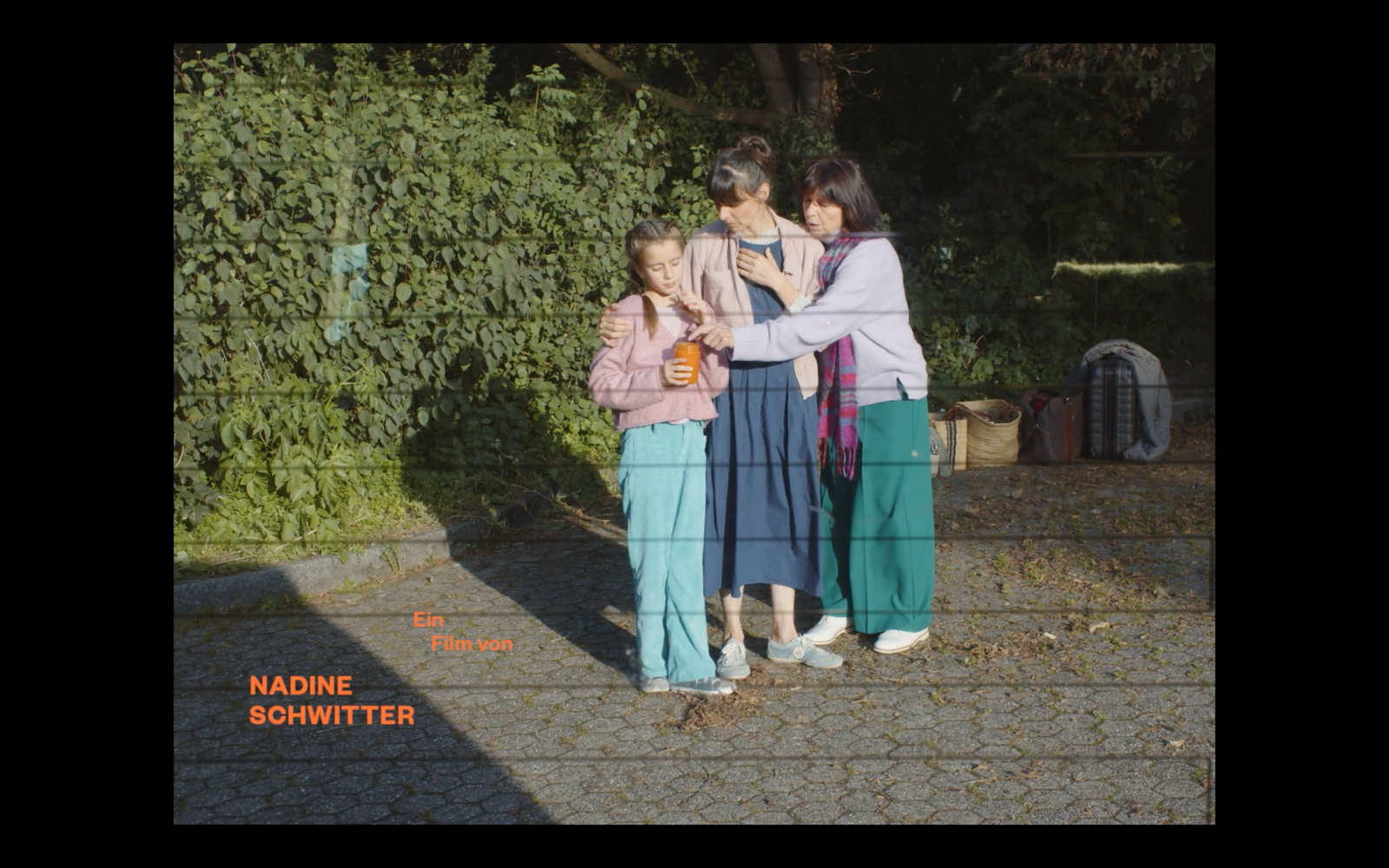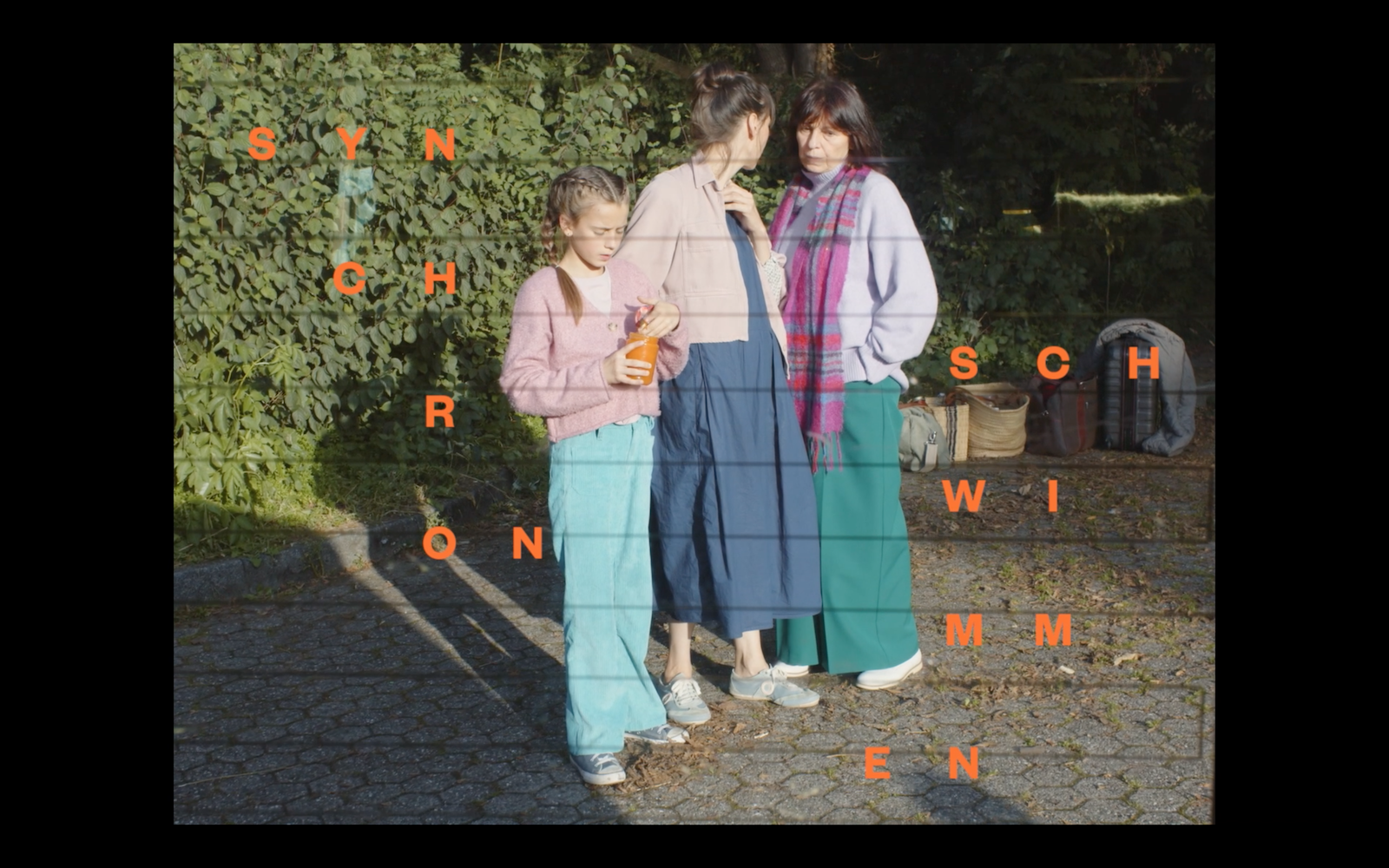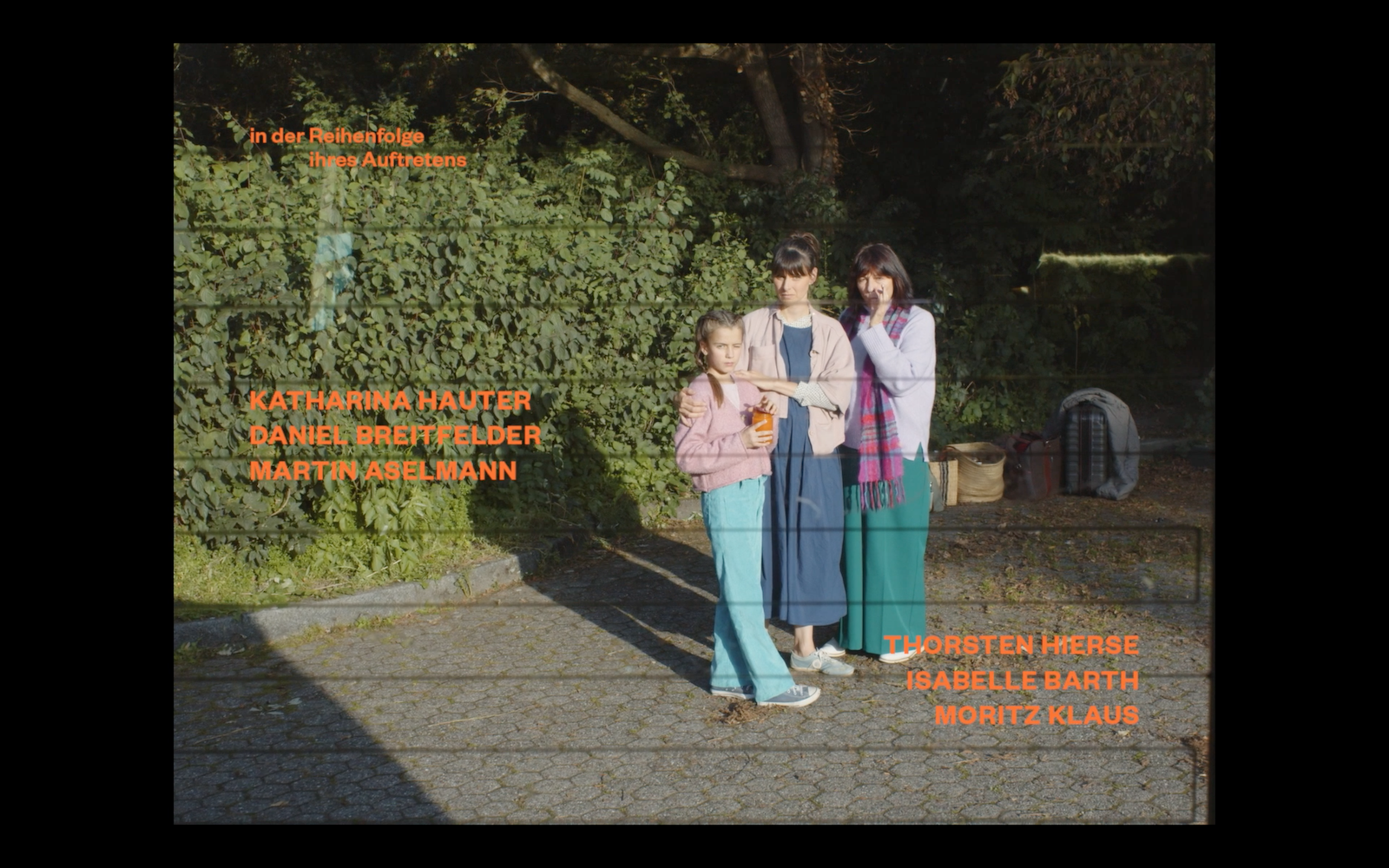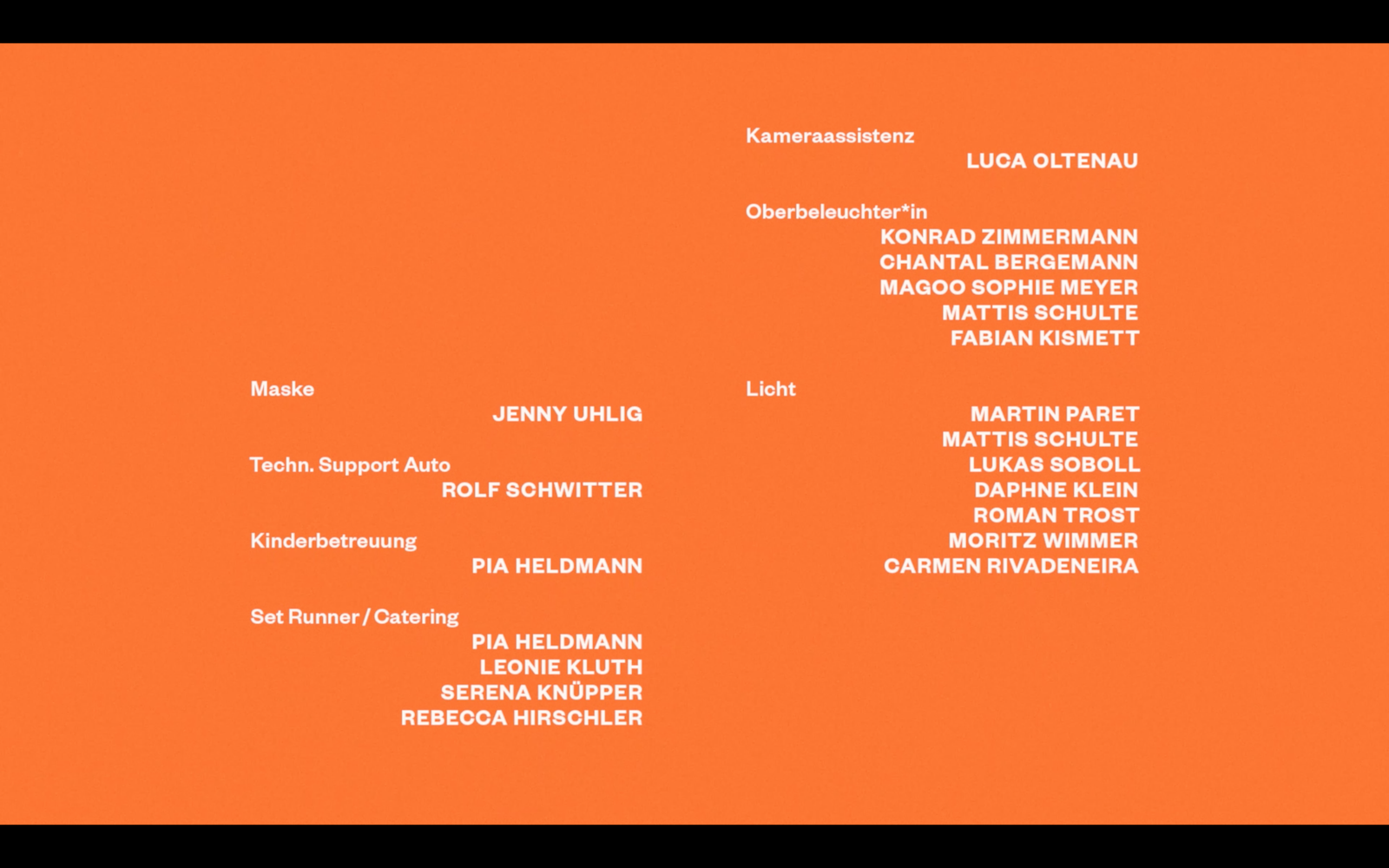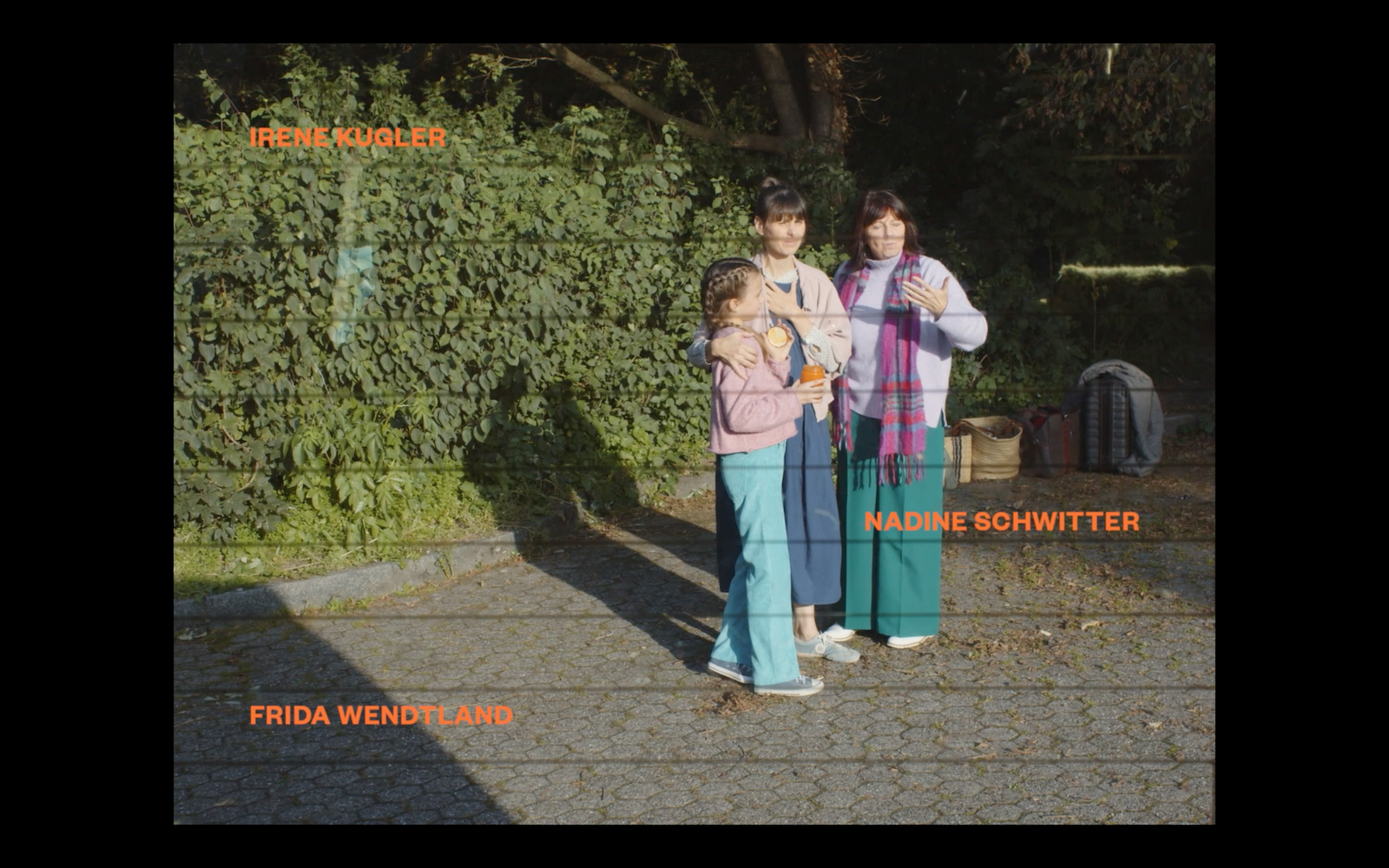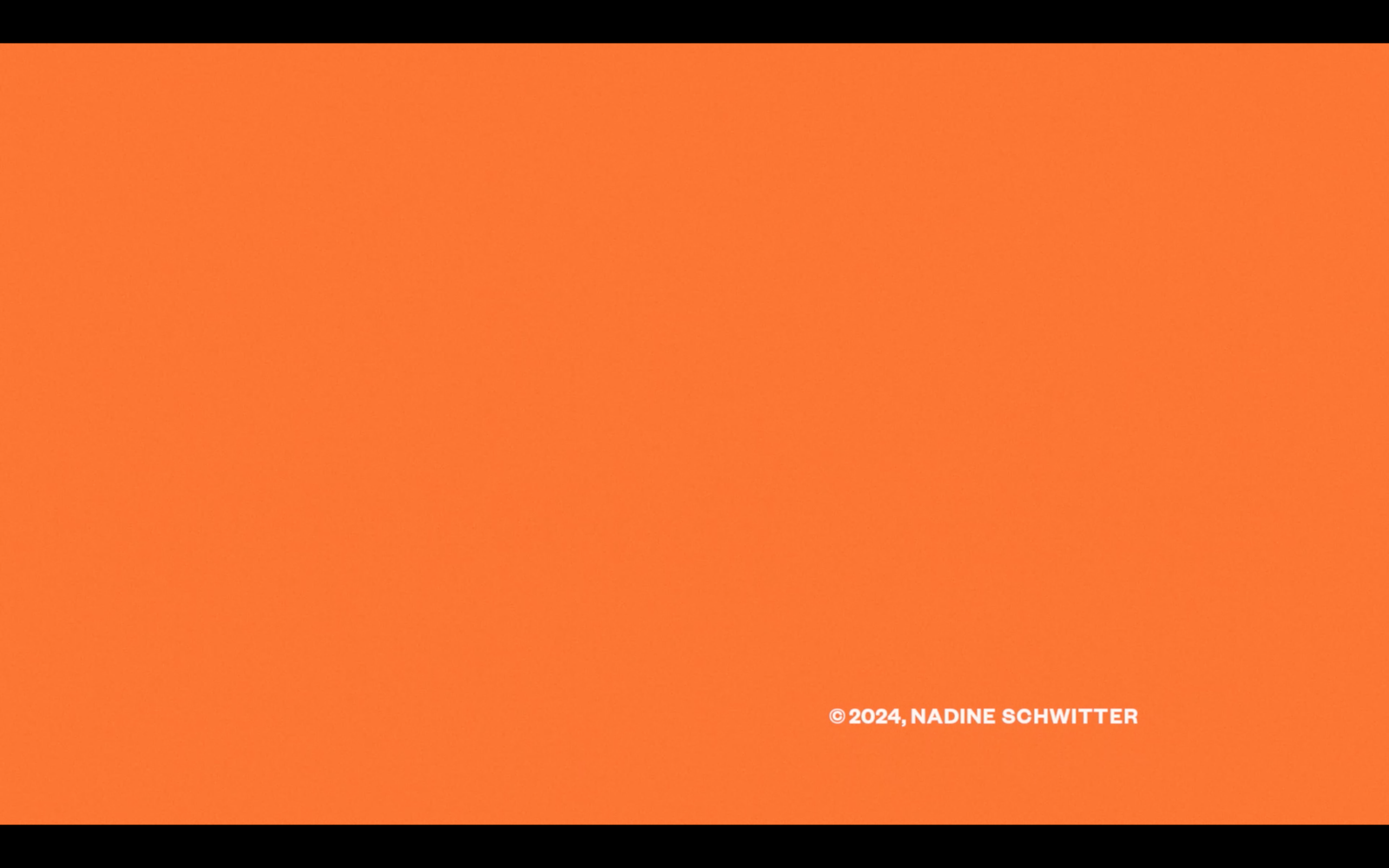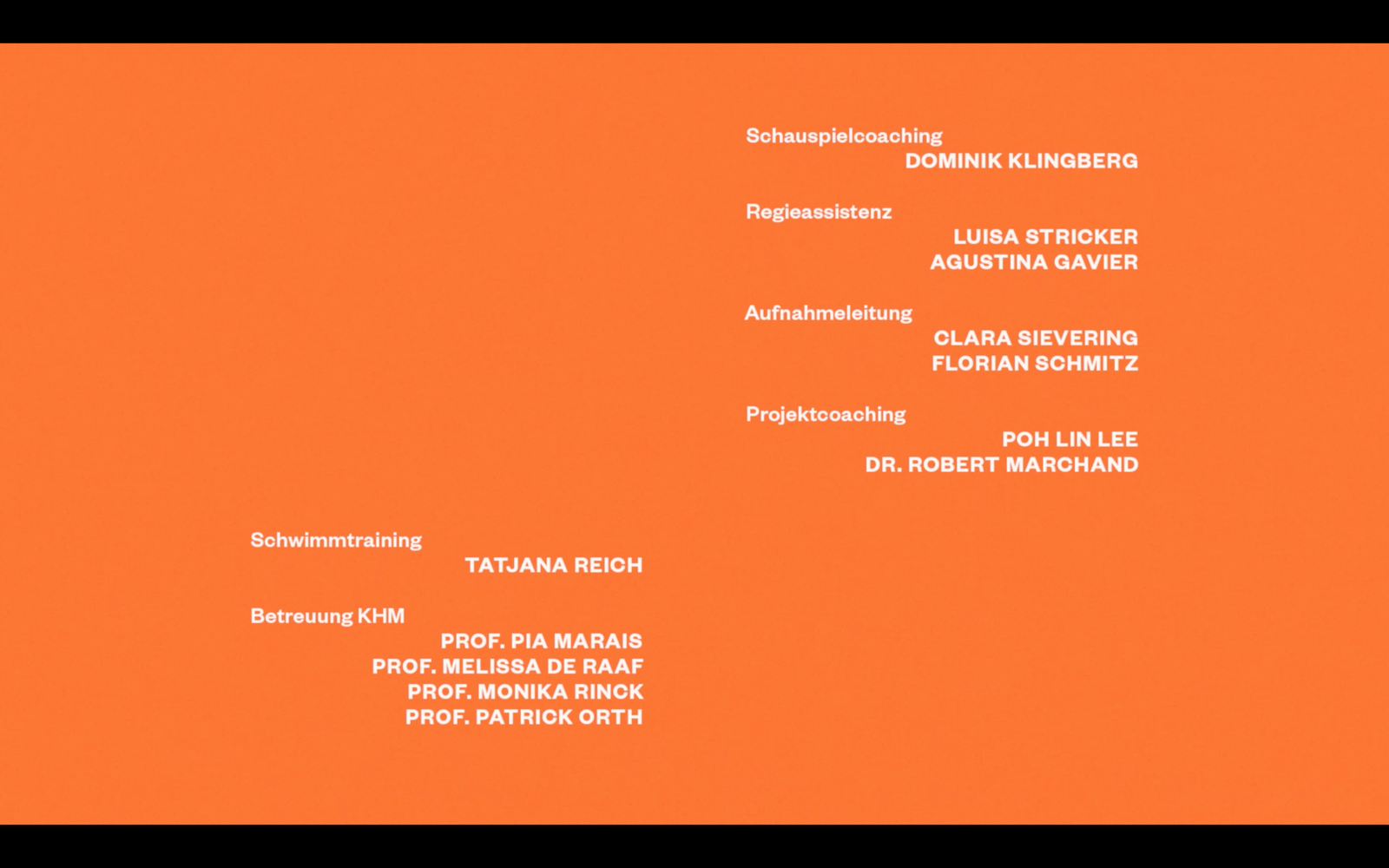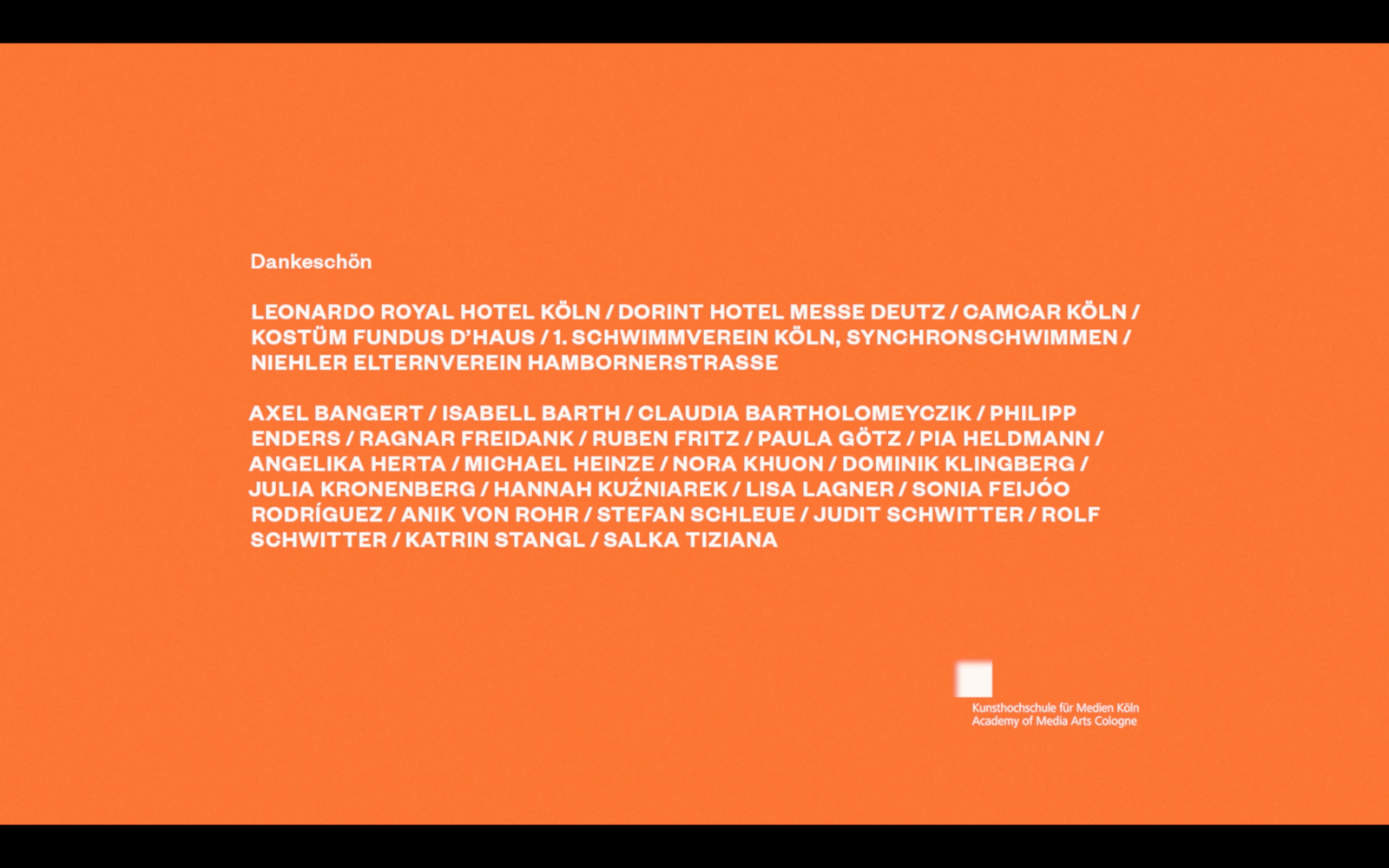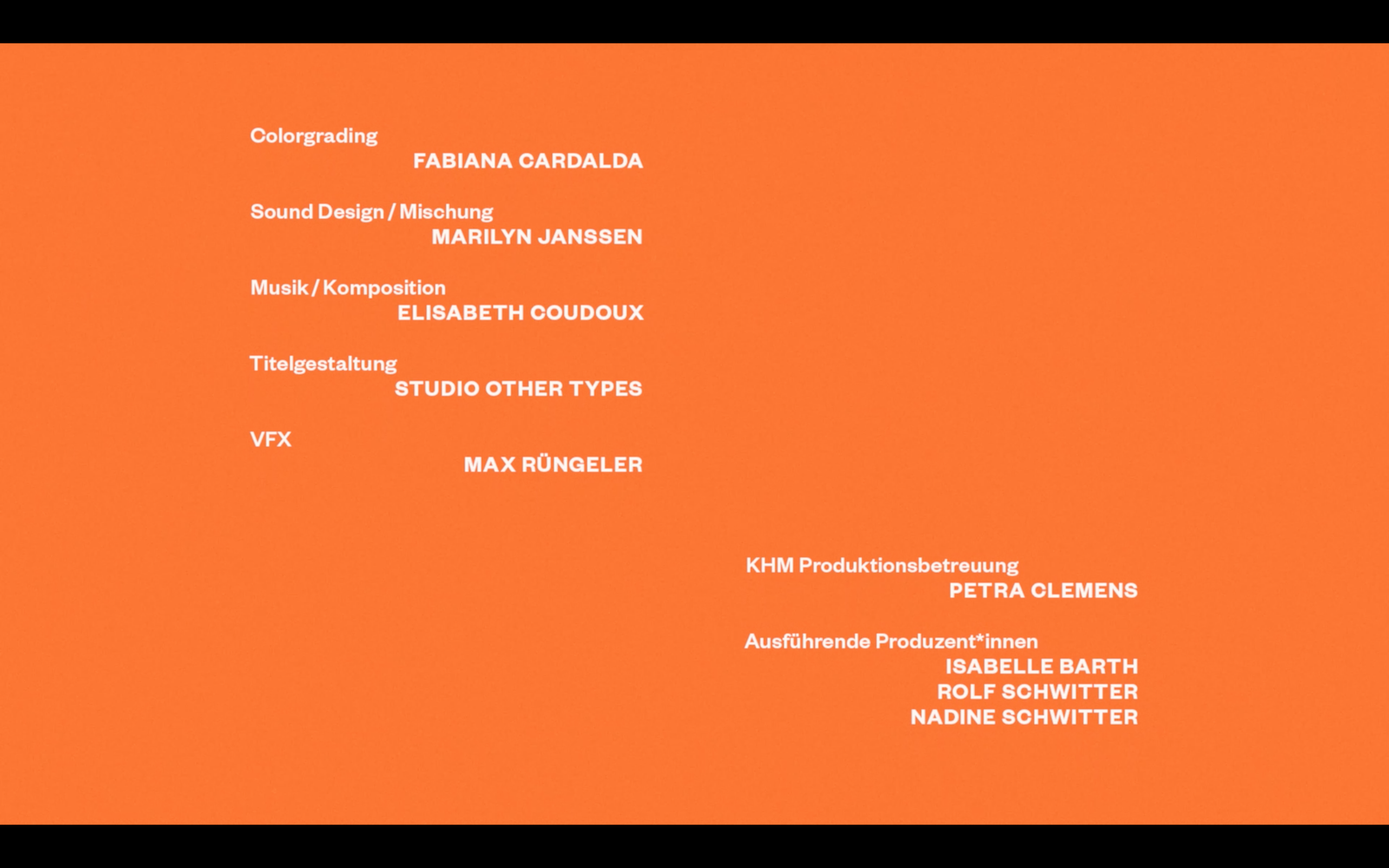
Synchronschwimmen
Film, Titel
Im Film Synchronschwimmen von Nadine Schwitter stranden Großmutter, Mutter und Enkelin auf dem Parkplatz eines Thermalhotels. Wegen eines Wasserschadens sitzen sie unerwartet im Auto fest — eingepfercht in beengtem Raum, bis der Pannendienst sie befreit.
Der Film wirft einen intensiven Blick auf die familiären Dynamiken zwischen den drei Generationen: gegenseitige Erwartungen, emotionale Abhängigkeiten, Machtspiele und die sehr unterschiedlich gelebte Verantwortung füreinander stehen im Zentrum der Erzählung.
Die Gestaltung der Titel ist modern und sachlich, erhält jedoch durch eine verspielte grafische Anordnung eine visuelle Leichtigkeit. Farblich greift sie Akzente aus dem Film auf und fügt sich so harmonisch in die Gesamterscheinung des Films ein.
Schrift: Founders Grotesk von Klim Type Foundry